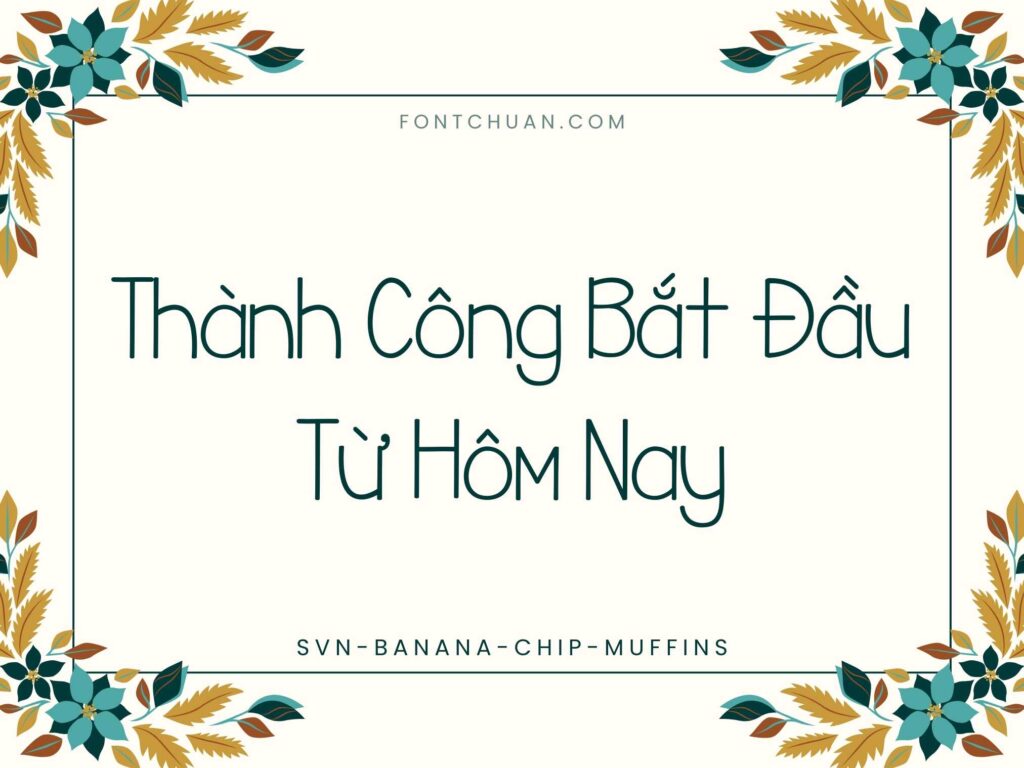
Font SVN Banana Chip Muffins Việt Hóa
Tác giả Font: Brielle Lang
Banana Chip Muffins là một font chữ viết tay vui nhộn và ngọt ngào, được thiết kế bởi Designs by Brielle và phát hành lần đầu vào năm 2015. Font này mang phong cách đơn giản nhưng đáng yêu, hoàn hảo cho các thiết kế như nhãn mác, logo và các dự án sáng tạo khác. Với 318 glyphs và 341 ký tự, Banana Chip Muffins hỗ trợ nhiều ngôn ngữ khác nhau, giúp mở rộng phạm vi sử dụng trên toàn cầu. Font đã được Việt hóa để hỗ trợ tiếng Việt bởi Styleno.1 Fonts, đồng thời được thành viên của Font Chuẩn sưu tầm và chia sẻ, đáp ứng nhu cầu của bạn đọc và ứng dụng thực tế vào các dự án thiết kế.
Đặc điểm thiết kế của Banana Chip Muffins bao gồm các đường nét viết tay đơn giản nhưng tinh tế, tạo cảm giác thân thiện và gần gũi. Font này phù hợp cho các ứng dụng như thiết kế nhãn mác, logo, thiệp mời và các dự án sáng tạo khác. Các ngành nghề phù hợp bao gồm quảng cáo, nghệ thuật và thiết kế đồ họa.